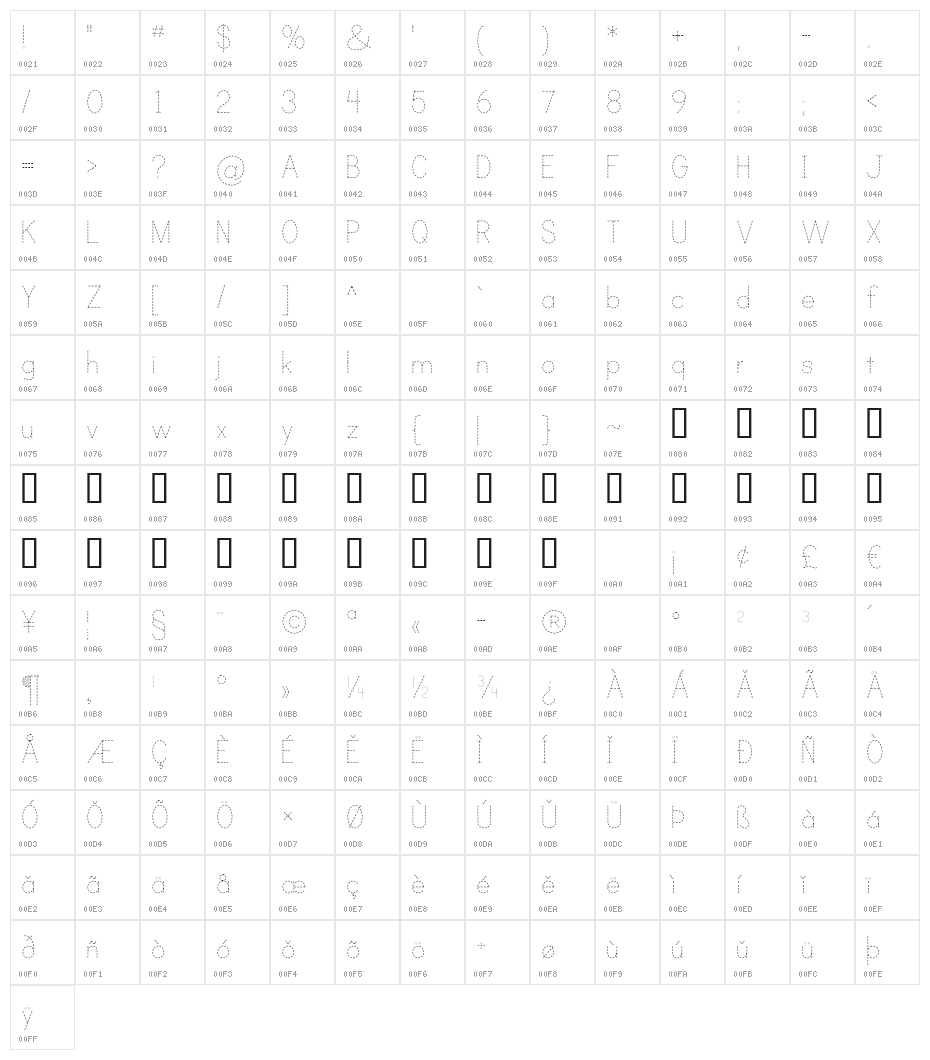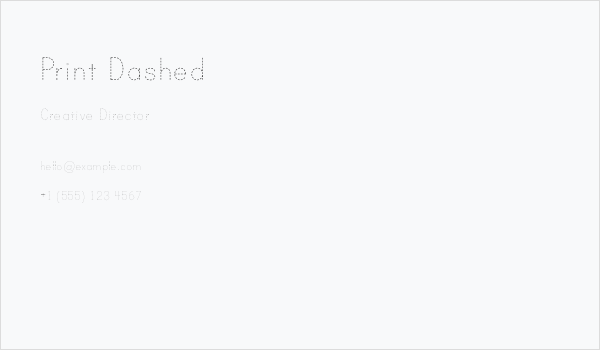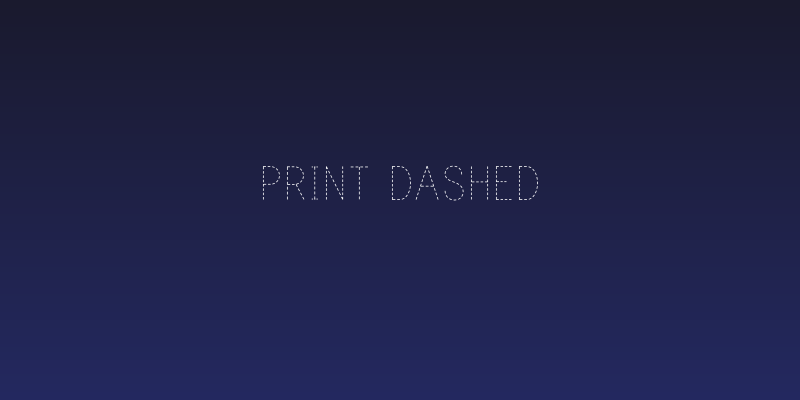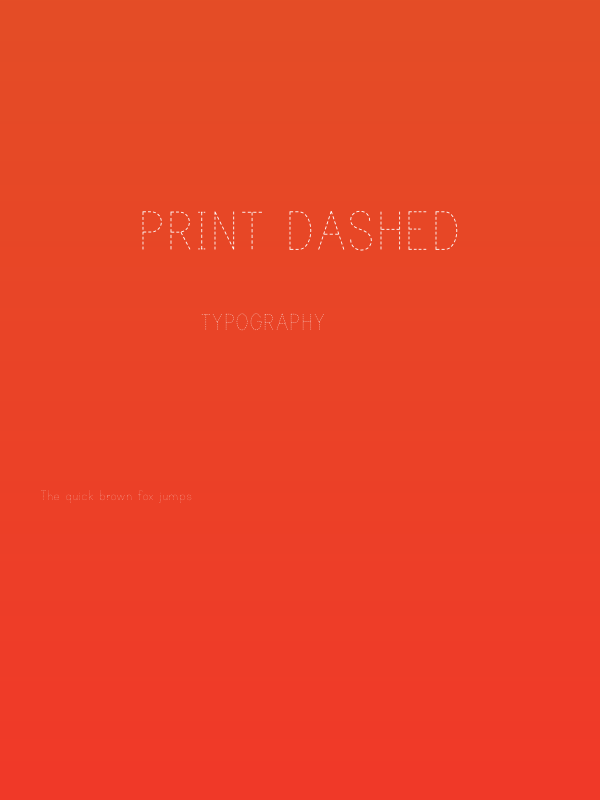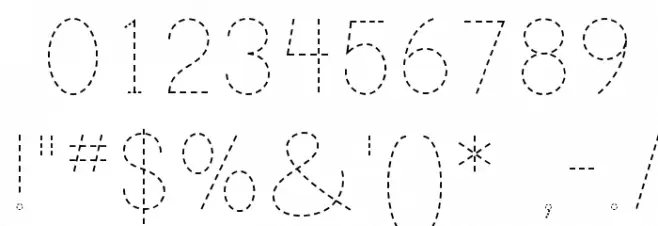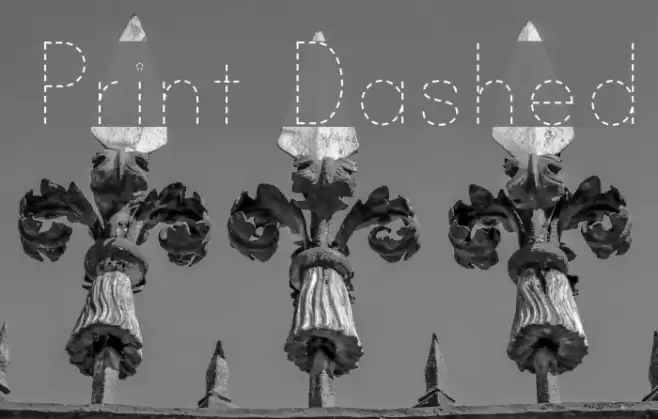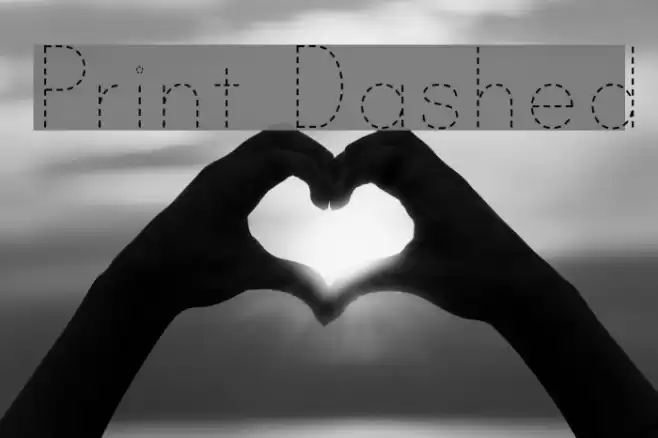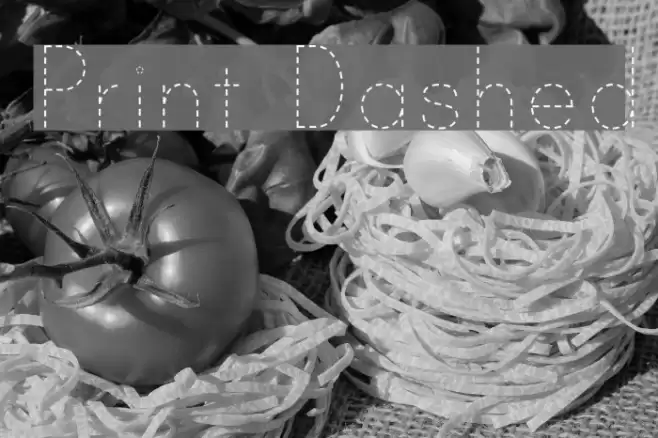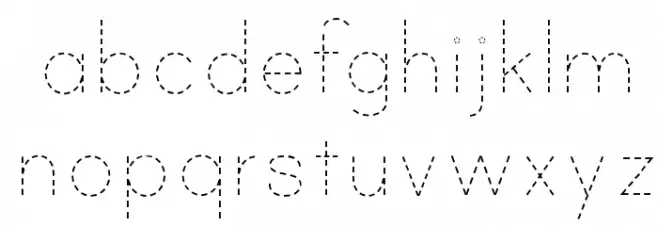
Print Dashed Font
✎ Sans Serif
| Категория | Sans Serif |
| Общий стиль | Modern, Playful |
| Область применения | Headlines, Logos, Creative Projects |
| Рекомендуемые проекты | Ideal for children's books, educational materials, playful branding, and creative posters. |